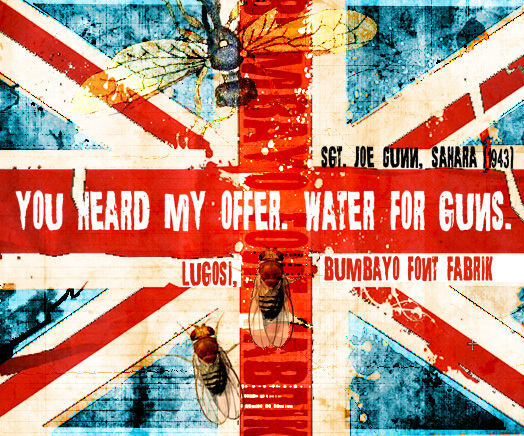
Lugosi to darmowy, horrorowy krój displayowy z efektem erozji, o wysokich, surowych literach, które wyglądają, jakby zostały wyrwane ze starego plakatu z potworami. Formy są ciężkie i proste, ale wyszczerbione krawędzie i poszarpane detale nadają wielkim literom niepokojący, dziki charakter.
Sprawdzi się na plakatach filmowych, ulotkach na Halloween, okładkach literatury pulp, gadżetach muzycznych i przy oprawie wydarzeń grozy. Tam, gdzie ten darmowy font potrafi zdziałać więcej za pomocą kilku słów niż jakikolwiek zwykły nagłówek. Użyj go do tytułów, okładek lub krótkich nazw marek, jeśli chcesz, by same litery niosły w sobie to wyblakłe, draculińskie zagrożenie.
Lugosi